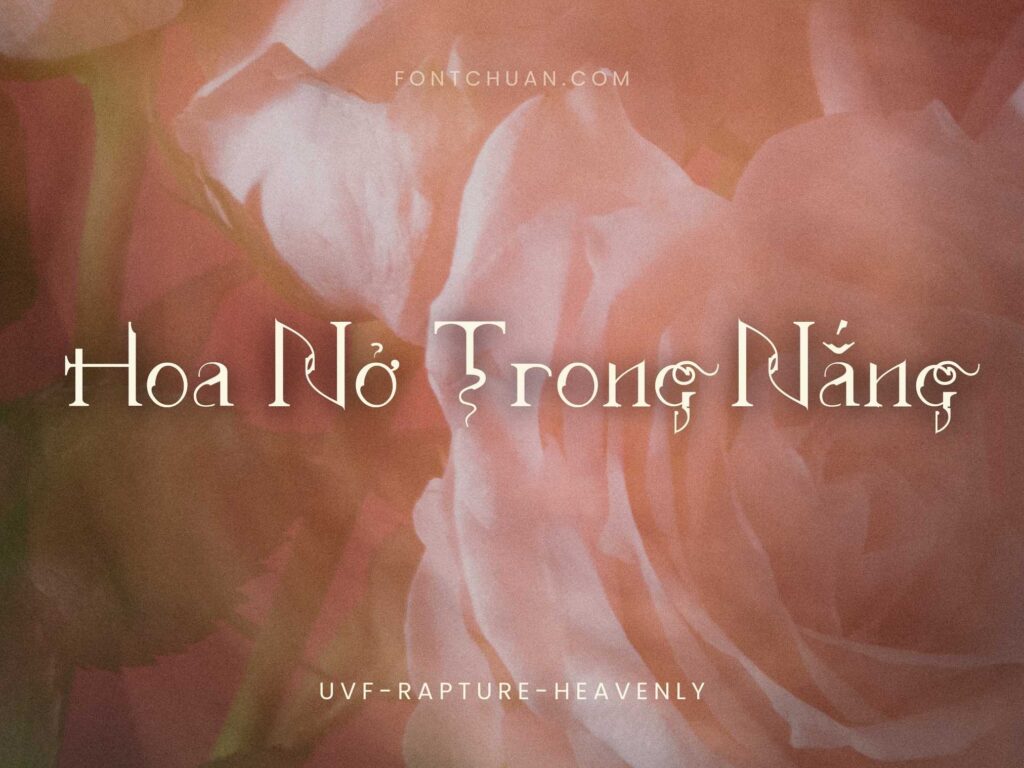
Font UVF Rapture Heavenly Việt Hóa
Rapture Heavenly là một font chữ script được thiết kế bởi Jason Tucker và phát hành bởi GarageFonts USA. Font này nổi bật với các đường nét mềm mại và uyển chuyển, tạo nên cảm giác thanh lịch và tinh tế. Với tổng cộng 327 ký tự, Rapture Heavenly cung cấp đầy đủ các ký tự cần thiết cho thiết kế sáng tạo. Đặc biệt, font này đã được Việt hóa, hỗ trợ đầy đủ các ký tự tiếng Việt, giúp người dùng tại Việt Nam dễ dàng sử dụng trong các dự án của mình.
Với thiết kế độc đáo và nghệ thuật, Rapture Heavenly phù hợp cho các ứng dụng như thiệp mời, tiêu đề sách, thiết kế logo và các ấn phẩm nghệ thuật. Trong lĩnh vực sự kiện, font này có thể được sử dụng trong các dịp như lễ hội, lễ cưới và các sự kiện văn hóa. Ngoài ra, Rapture Heavenly cũng thích hợp cho các ngành nghề như thiết kế đồ họa, nghệ thuật trang trí và xuất bản.